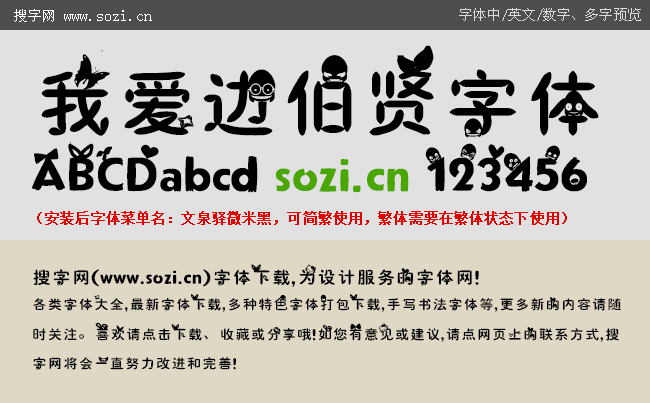
我愛邊伯賢字體
搜字網(wǎng)給大家提供一款很有趣的手機(jī)中文字體下載。我愛邊伯賢字體,這款手機(jī)字體是在漢儀橄欖體簡體字體筆畫間插入了可愛蝴蝶卡通圖案。趣味性實(shí)足,該手機(jī)字體個(gè)性實(shí)足,趣味性強(qiáng),又保持了文字的識別度,特別適合喜歡手機(jī)字體個(gè)性一些的朋友在手機(jī)上安裝使用。